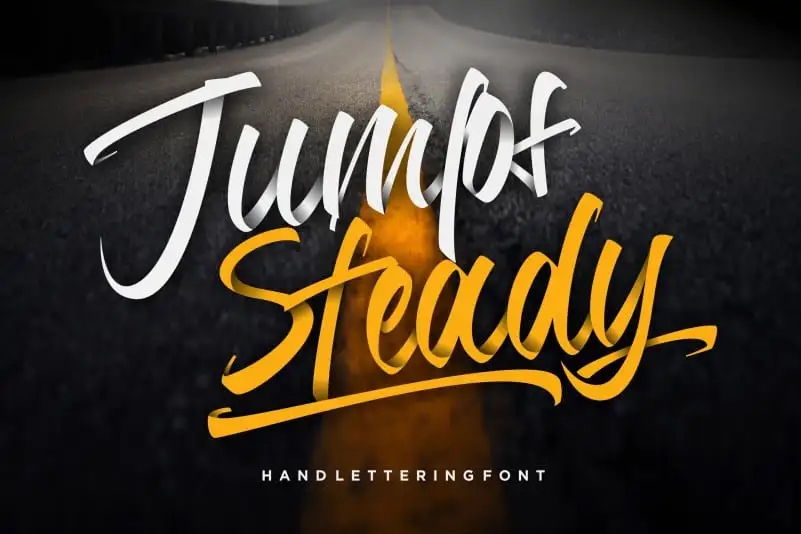
Jumps Steady Calligraphy Font – Fonte Grátis
Jumps Steady Calligraphy Font
Bem-vindo a uma nova descoberta no mundo das fuentes! Se você é apaixonado por letras manuscritas elegantes e contemporâneas, esta fonte Script Jumps Steady Calligraphy pode ser perfeita para o seu próximo projeto criativo. Inspirada em belos desenhos de caligrafia clássicos que continuam a vibrar com modernidade, essa fonte escrita à mão apresenta um equilíbrio perfeito entre traços finos e grossos, dando-lhe o toque necessário para seus trabalhos luxuosos. Seja para adicionar um toque autêntico em sua próxima peça de arte ou projeto editorial, Jumps Steady é ideal para quem busca beleza e sofisticação. Aproveite seu download da fonte para tornar suas criações ainda mais únicas. Descubra o poder das fuentes 1001fonts hoje!